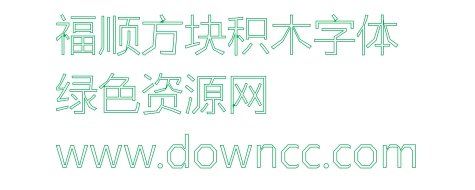
福順?lè)綁K積木字體
福順?lè)綁K積木字體是一款設(shè)計(jì)十分巧妙的空心字體,采用了端正的方塊形狀拼湊的筆畫(huà),讓字體呈現(xiàn)端正的宋體模樣,鏤空的設(shè)計(jì)也讓文字變得清晰大方起來(lái),用來(lái)logo制作再適合不過(guò)了,快來(lái)綠色資源網(wǎng)試試吧!
方塊積木字體特色
方塊積木字體向來(lái)給人過(guò)于粗糙和笨拙的感覺(jué),而福順的這款字體用細(xì)膩的線條勾勒出圓潤(rùn)的筆畫(huà)或字母,打破了這種沉重,增加了自己的趣味和特色。